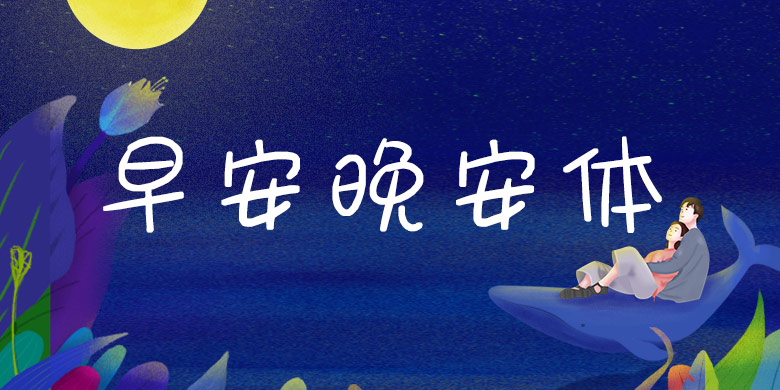
方正手迹-早安晚安体
字体品牌: 方正手迹 设计师:俞亦婷 字体分类:创意书写 字体属性:精品字 字符集:大陆简体(GB2312-80) 发布时间: 2018
早安晚安体,字形大胆做夸张处理,转折处方圆交替使用,搭配俏皮简单的线条,使得整个字体与众不同,个性十足。适用于青少年儿童类书刊、漫画综艺字幕、品牌广告和产品包装设计,以及社交网络的个性化用字。